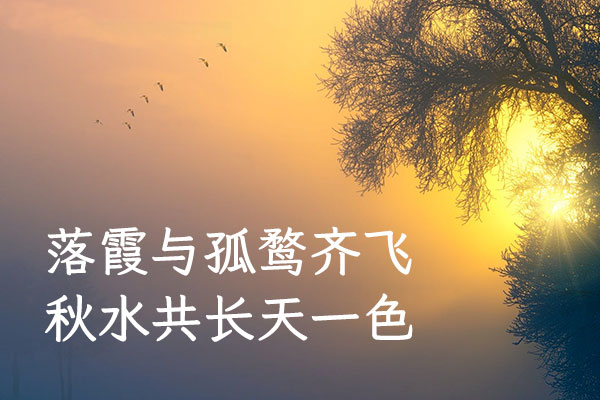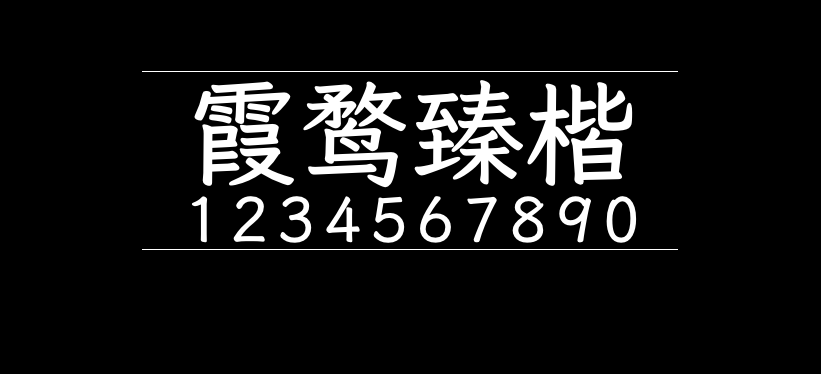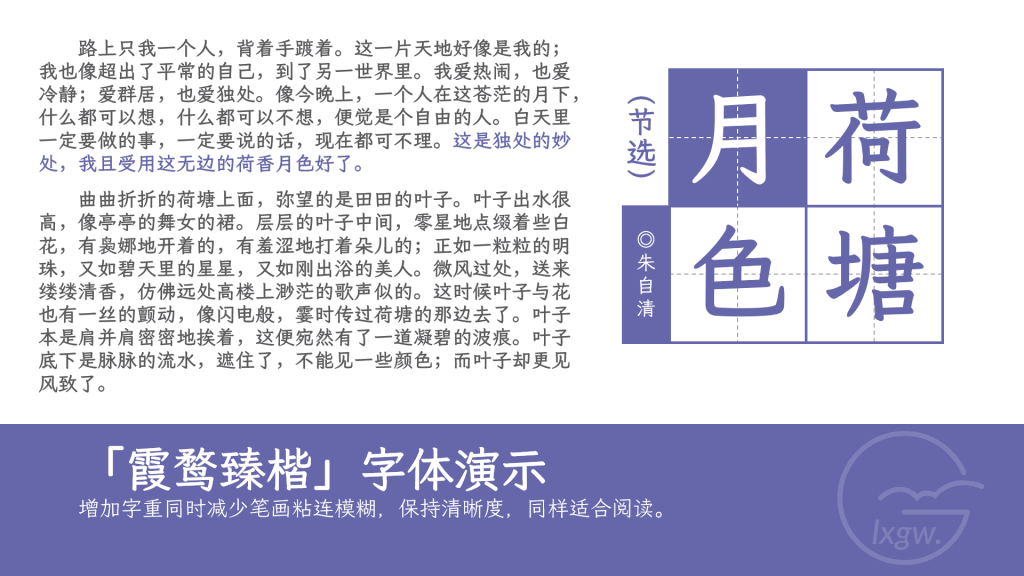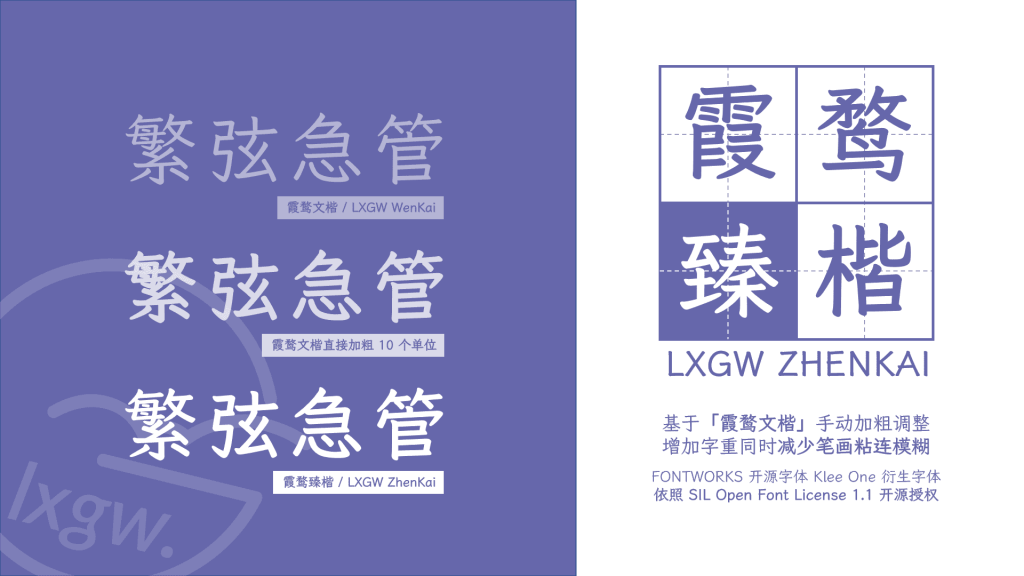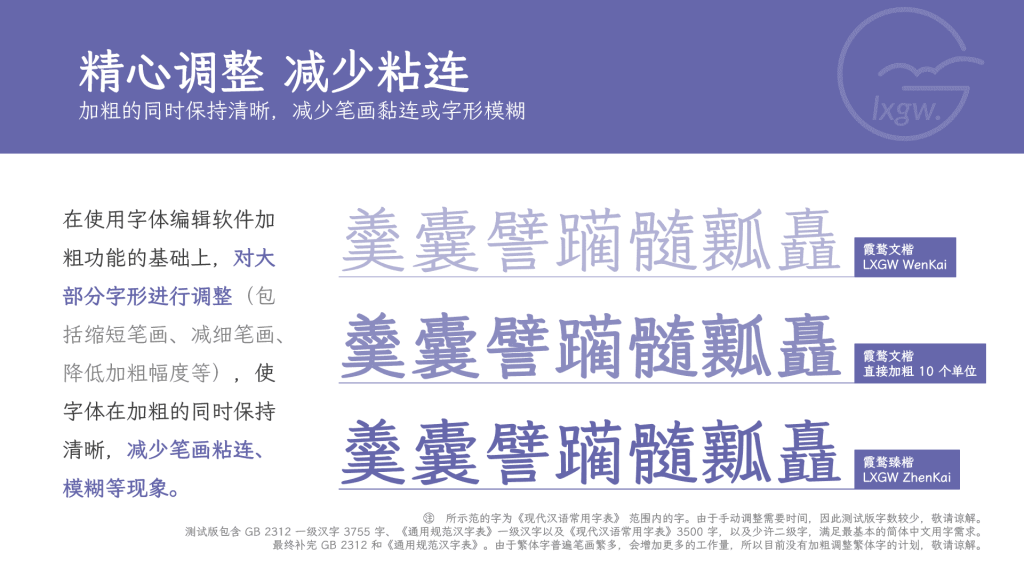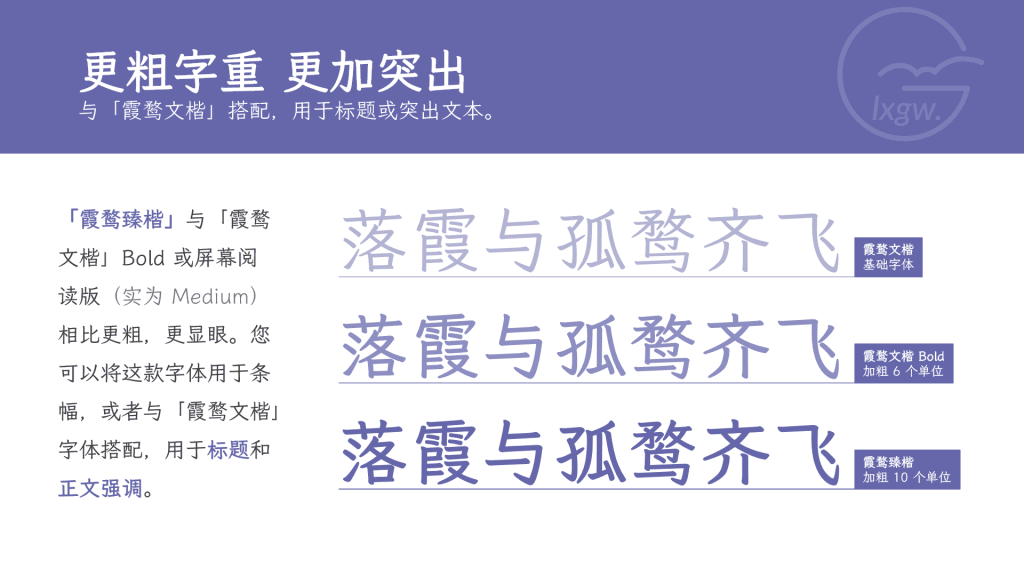
霞鹜臻楷
霞鹜臻楷是作者孤鹜先森对霞鹜文楷进行粗字重的制作尝试。由于目前霞鹜文楷 Bold 字重(实为 Medium,也是「霞鹜文楷屏幕阅读版」 的常规字重)对部分用户来说依然比较细,在图形软件中直接对字体描边加粗的话,部分字形会糊成一片。因此开始了霞鹜臻楷这个项目,在使用字体编辑软件加粗功能的基础上,对大部分字形进行调整(包括缩短笔画、减细笔画、降低加粗幅度等),使字体在加粗的同时保持清晰,减少笔画黏连、模糊、毛刺等问题。自由君已经帮大家试过了,果然很粗效果很好!
需要注意的是,霞鹜臻楷未覆盖GB2312的所有字形,这意味着部分不常见的字会存在缺字现象,不过作者更新速度也快,隔几天就会发布一个新版本,相信很快就会完成。